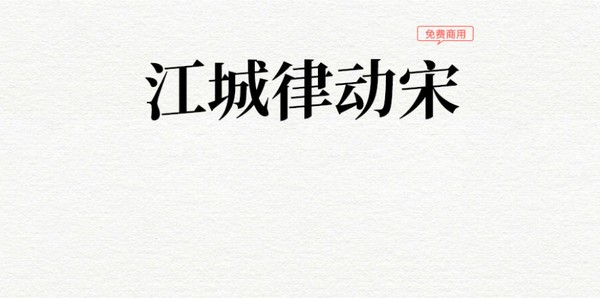
江城律动宋字体
江城律动宋字体介绍:
江城律动宋是大神@刘鹏基于思源宋体CN-Bold向上倾斜5度改造的一款字体。江城律动宋字体向上倾斜,上下律动,自带活动促销BGM,天生适用于活动、促销等广告语,适当缩小字间距效果更佳哦。
江城律动宋体特点:
这款字体与猫啃网之前发布的@新愚公制作的猫啃网风雅宋有点类似,@刘鹏和@新愚公他们的想法创意都想到一块了,就是把字体向上倾斜,让字体有了一种动感。江城律动宋与猫啃网风雅宋的不同之处在于,两款字体向上倾斜的角度不一样,江城律动宋的倾斜度会更高一点,而猫啃网风雅宋就是微微一突很倾城。另外猫啃网风雅宋对字体进行压缩,感觉会修长一点,并且字体重心会也感觉更高了。同样的字号,风雅宋会字会更小一点。